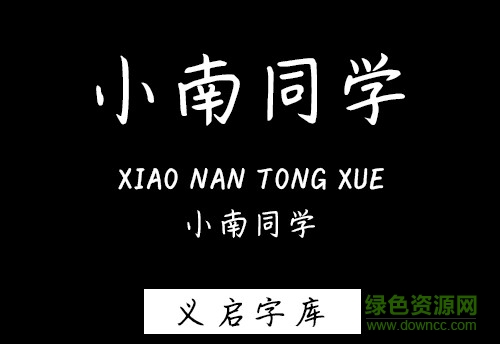
義啟小南同學(xué)體是義啟字庫里的一款特色手寫體,這款義啟字體字形端正大方,筆鋒細(xì)膩,看起來非常的舒適,應(yīng)用領(lǐng)域也非常的廣泛,需要的朋友歡迎來綠色資源網(wǎng)下載使用!
1、手寫風(fēng)格,沒有裝飾,比較干凈;
2、字體簡(jiǎn)潔、辨識(shí)度高;
3、筆畫粗細(xì)適中,應(yīng)用廣泛。